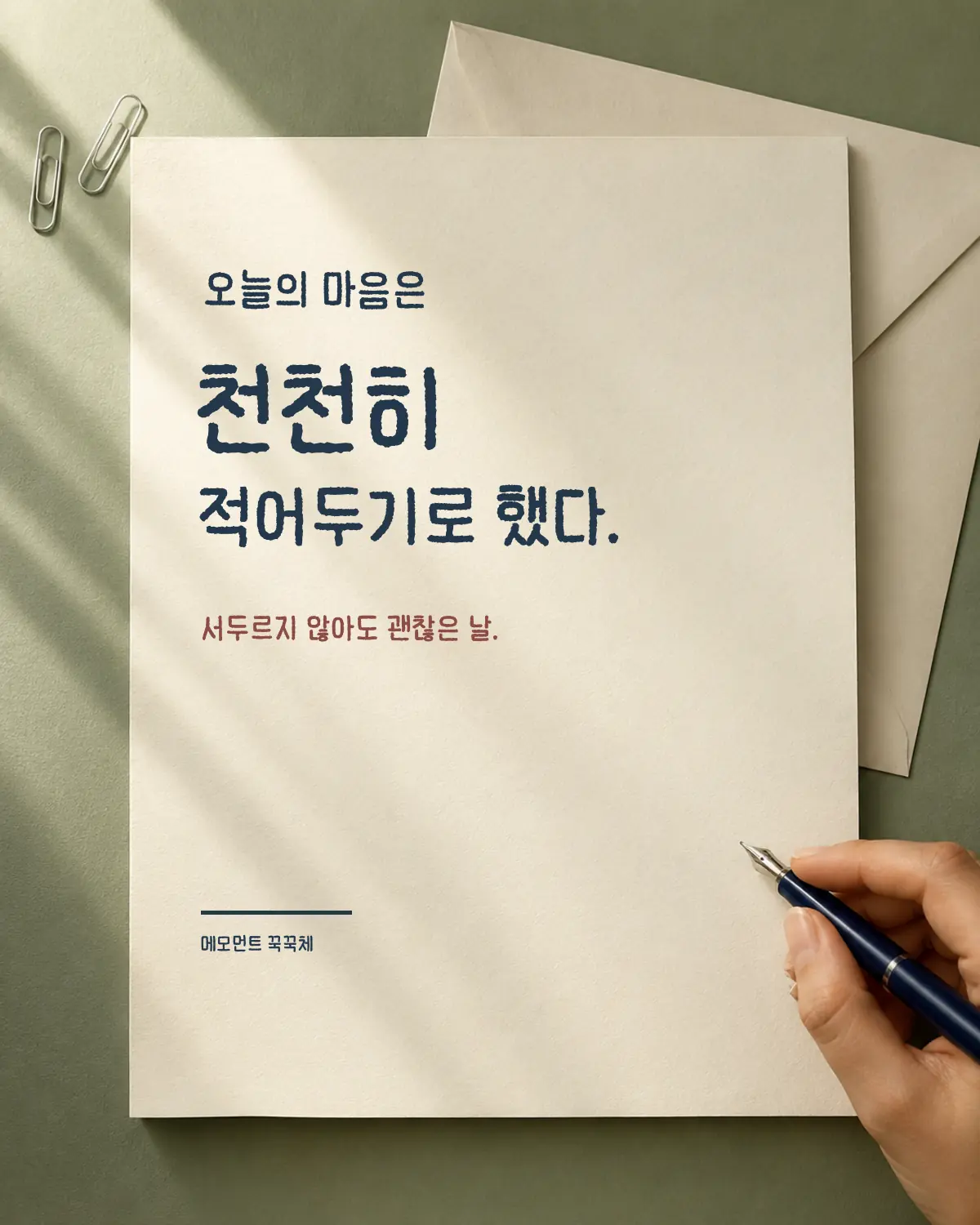
메모먼트 꾹꾹체 — 메모먼트에서 배포하는 무료 폰트입니다. 손으로 꾹꾹 눌러쓴 듯한 질감과 단정한 리듬이 어우러진 손글씨체
인공지능 기록 앱을 만드는 메모먼트가 2025년에 내놓은 손글씨 서체입니다. 이름의 유래를 제작사가 한 줄로 밝혀 두었습니다. 기록은 마음을 꾹꾹 눌러 담는 일이니까요.
제작사가 설명하는 조형은 이렇습니다. 손글씨를 바탕으로 하되 디지털 화면에서도 읽기 쉽도록 자간과 획의 균형을 조정했고, 단정하면서도 따뜻한 인상을 주는 형태로 완성했다는 것입니다. 숨겨 둔 재미도 하나 있습니다. ♧ 기호를 입력하면 고양이 발바닥이 나타납니다.